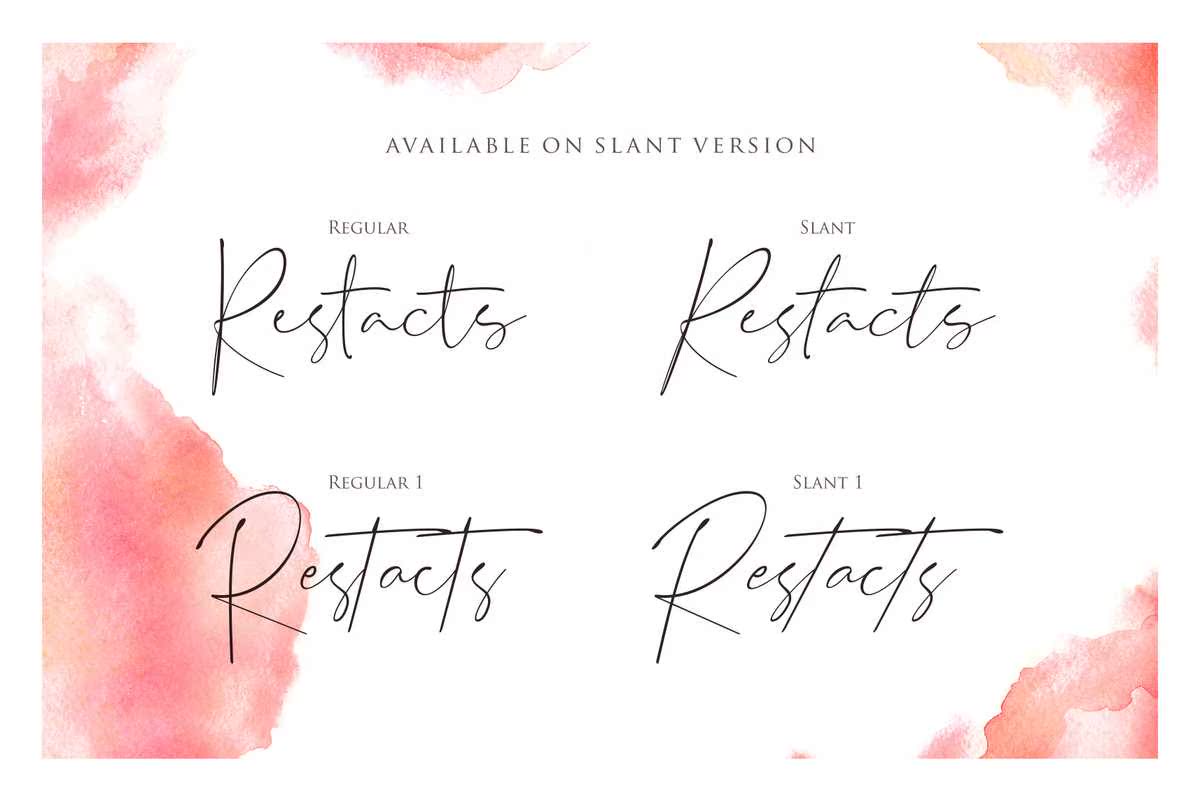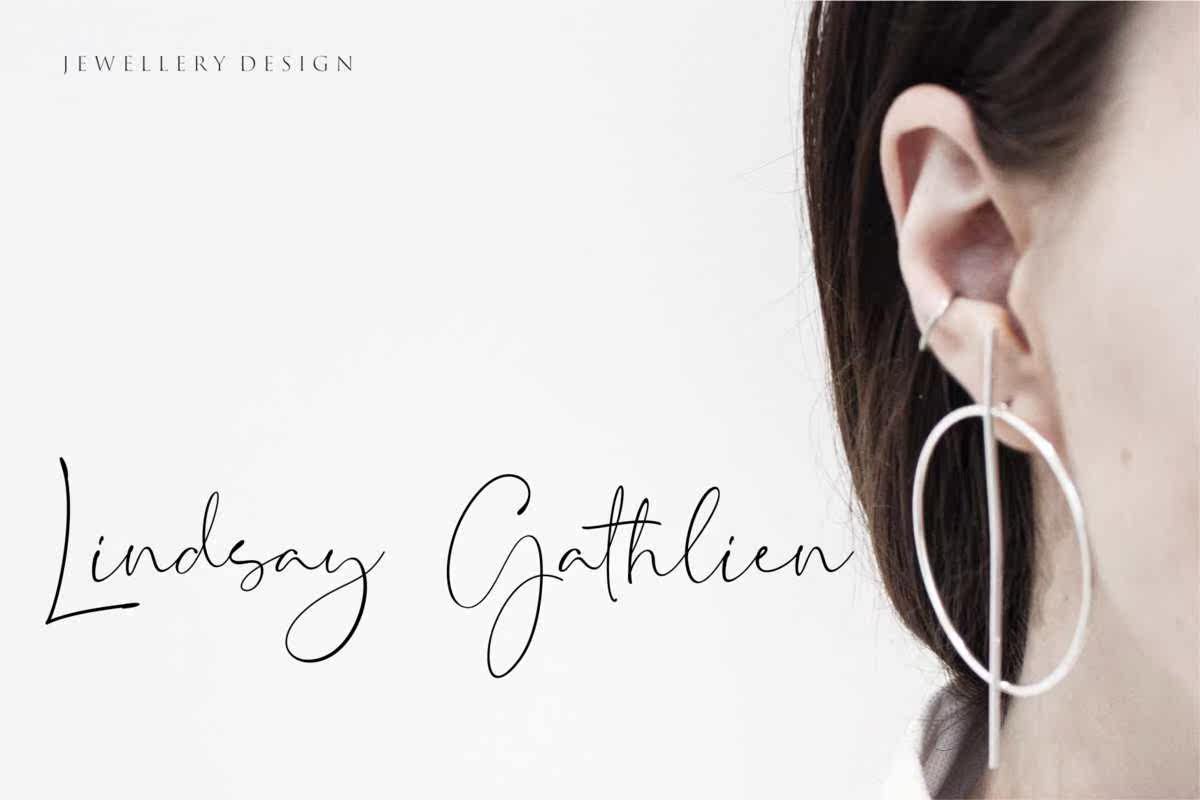
介绍StactScript,这里我们提供了2个变体,第一个变体的描述更为随意,第二个变体的描述更为优雅和粗体。这两个变体看起来都很平滑,您可以查看我们的预览了解更多详细信息。重新发布的描述为任何设计项目提供了美丽的文字表达,包括品牌、社交媒体、徽标、婚礼宣传、照片覆盖、,等等。介绍StactScript,这里我们提供了2个变体,第一个变体的描述更为随意,第二个变体的描述更为优雅和粗体。这两个变体的外观更为平滑,您可以查看我们的预览以了解更多细节。重述脚本为任何设计项目提供了美丽的文字表达,包括品牌、社交媒体、徽标、婚礼宣传、照片覆盖等。